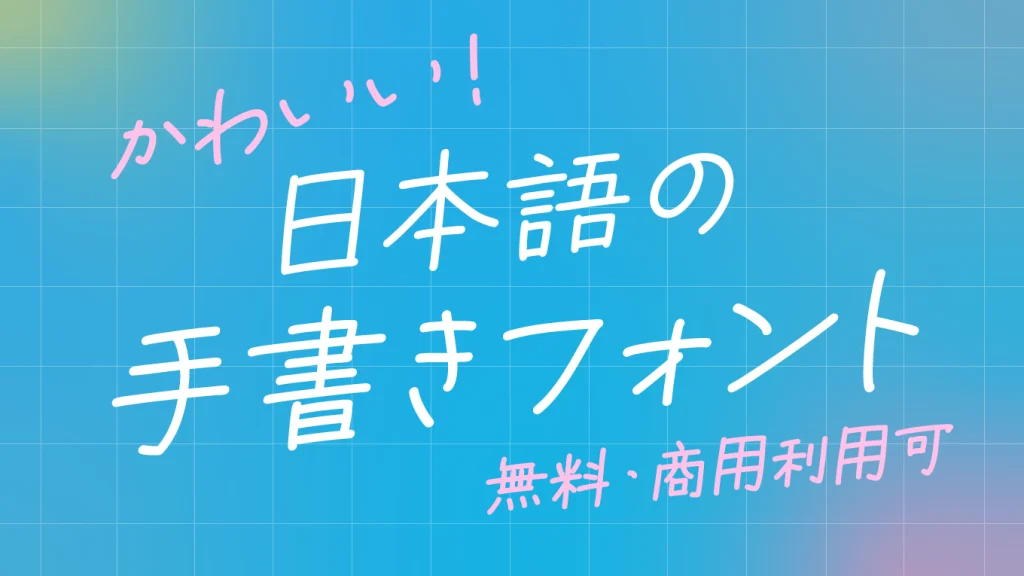
かわいい日本語の手書きフォント30選【商用可】
本記事では、おしゃれでかわいい日本語の手書きフォントをご紹介します。 手書きの日本語フリーフォントは数多く公開されており、作り手によって文字の個性や雰囲気が大きく異なります。やさしく可愛らしい女性的な手書き文字から、ラフ hellip; 続きを読む かわいい日本語の手書きフォント30選【商用可】